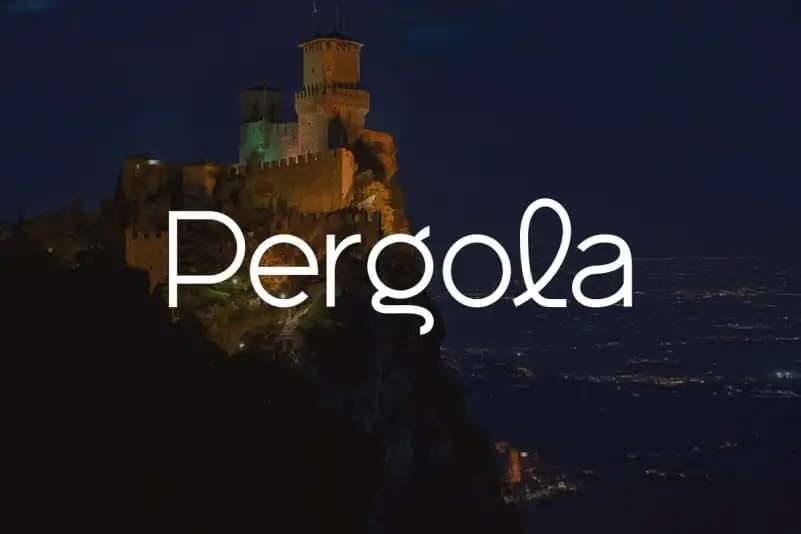
Pergola Sans Serif é uma elegante fonte de tipo sans serif que se destaca por sua simplicidade e sofisticação. Perfeita para estilos contemporâneos, a Pergola pode ser usada com sucesso em marcas fashionistas, revistas femininas ou conteúdos relacionados ao estilo de vida das mulheres. Esta fonte traz uma dose de frescura que certamente vai deixar seu projeto mais atrativo e moderno. Para designers buscando um tipo sofisticado e contemporâneo sem perder a elegância, Pergola é a escolha perfeita. Combinada com as cores vibrantes e formas geométricas típicas do estilo fashionista, esta fonte promete tornar seus projetos ainda mais chamativos e estilizados.